10 кириллических шрифтов, чтобы подписывать открытки и подарки
Не все из нас обладают идеальным почерком, да и вообще любят писать от руки. Для тех, кто хотел бы набирать открытки, приглашения и бирки для подарков на компьютере, мы выбрали десять бесплатных шрифтов с поддержкой кириллицы.
Charming
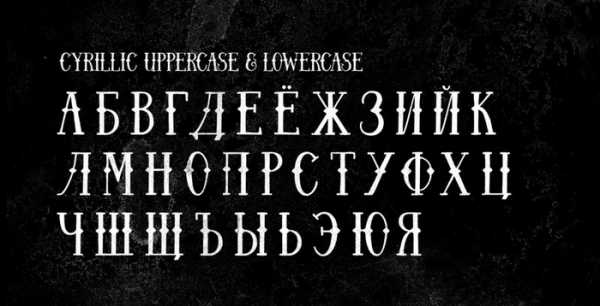
Komi
Этнический шрифт. Таким хорошо подписать открытку, прилагающуюся к набору травяных чаев.
Iced tea
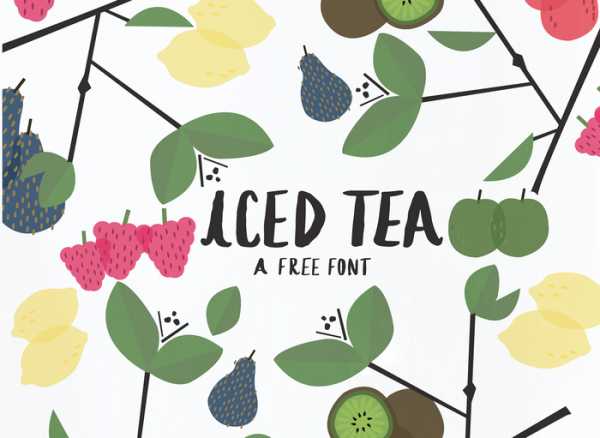
Оптимистичный и простой шрифт, которым можно и рукодельный подарок подписать, и мотивирующий постер набрать.
Katona
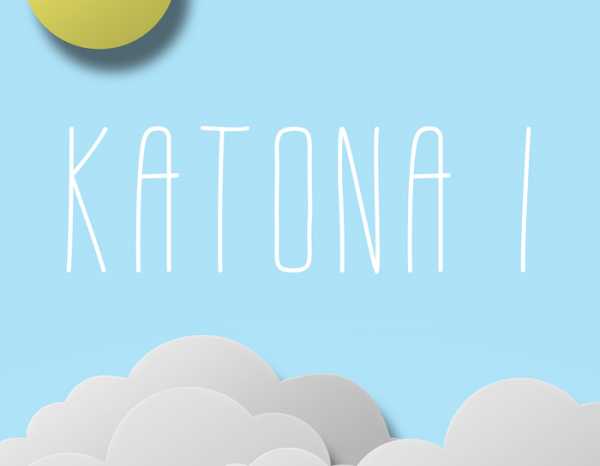
Еще один рукописный шрифт, на этот раз — тонкий и нежный, очень «открыточный».
Peteroque
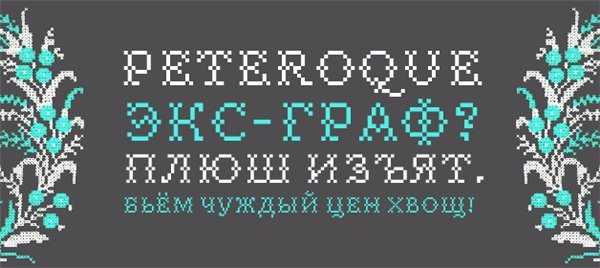
Вышитые крестиком буквы для самых душевных поздравлений и приглашений.
Legend
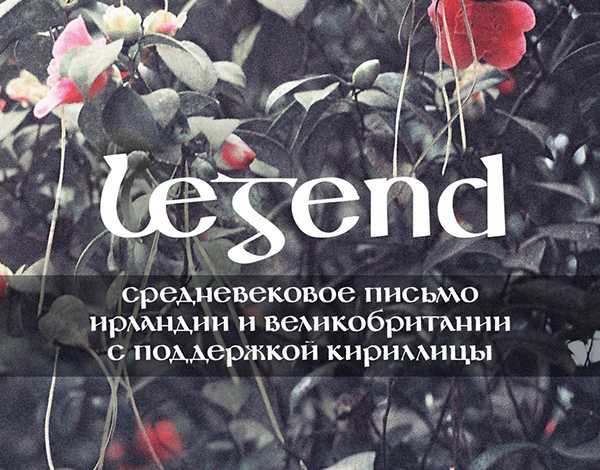
Средневековый шрифт для тематических подарков и вечеринок. Впрочем, как и остальные, его можно использовать без особого повода, ведь нам, в отличие от серьезных дизайнеров, можно «играть со шрифтами» как угодно.
Barkentina
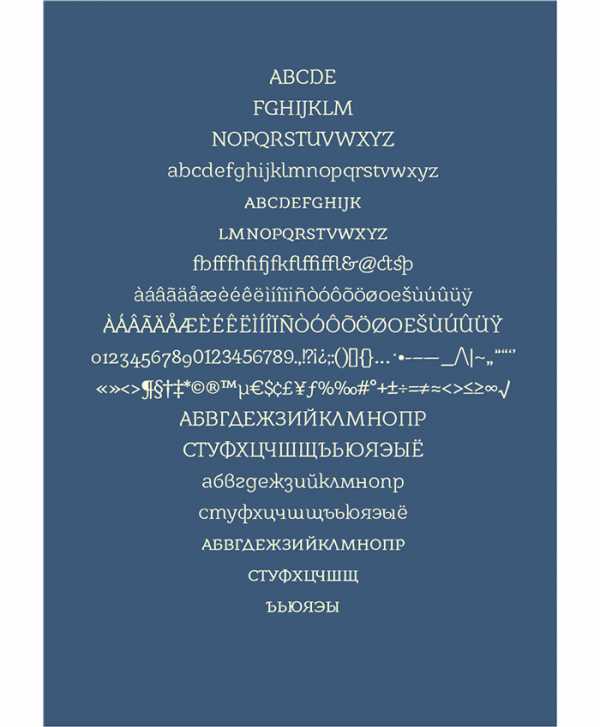
Элегантный шрифт для материалов в стиле ар-деко — так описывают его создатели. Понравится взрослым людям с хорошим вкусом.
Metropolis 1920
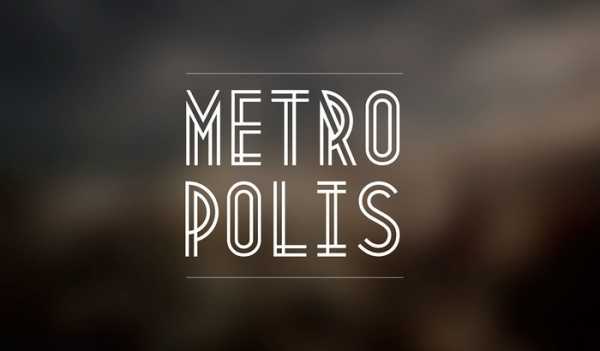
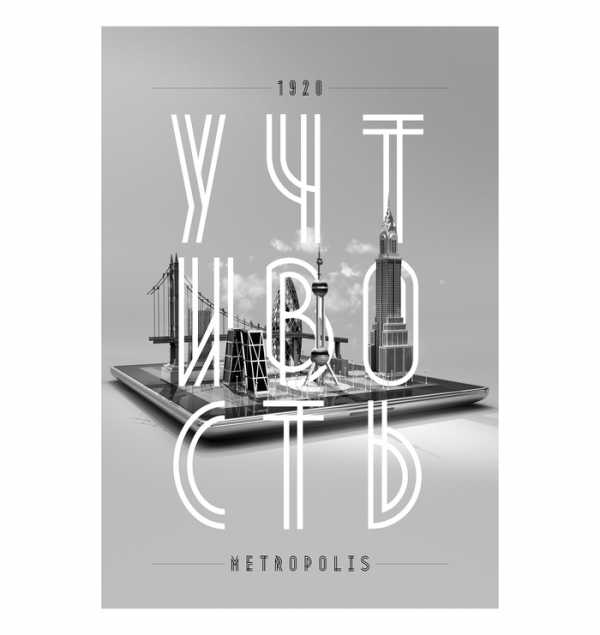
А вот это уже очевидное ар-деко: огни большого города, небоскребы, шикарная жизнь. Используйте, если собираетесь закатить вечеринку в стиле «Великого Гэтсби».
Douchepac
Экспериментальный иронический пиксельный шрифт, будто специально созданный для приглашений. Пробуйте разные цвета и сочетания обычного и жирного начертания.
Chehov
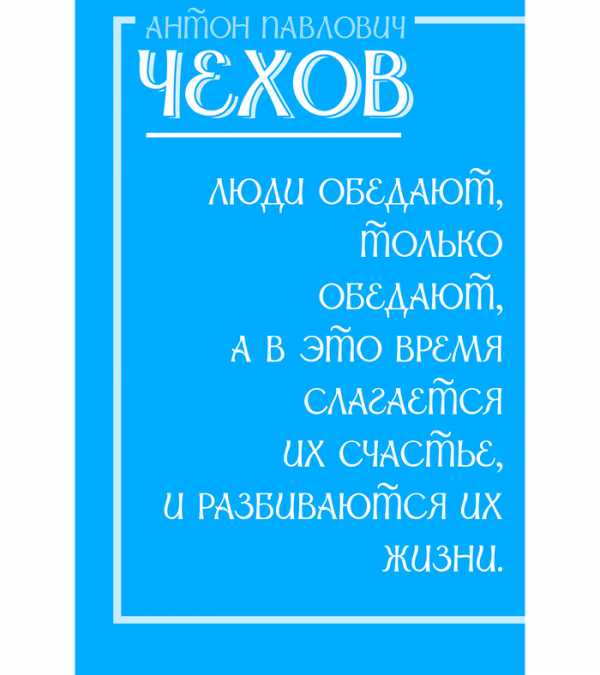
Русский шрифт, созданный специально для кириллицы. К сожалению, из знаков препинания только точка и запятая.
Chava
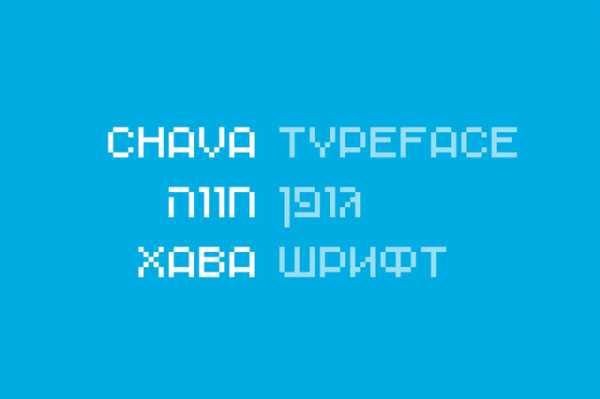
И еще один пиксельный шрифт, попроще, чем Douchepac.
(бесплатный шрифт (free font), латиница)